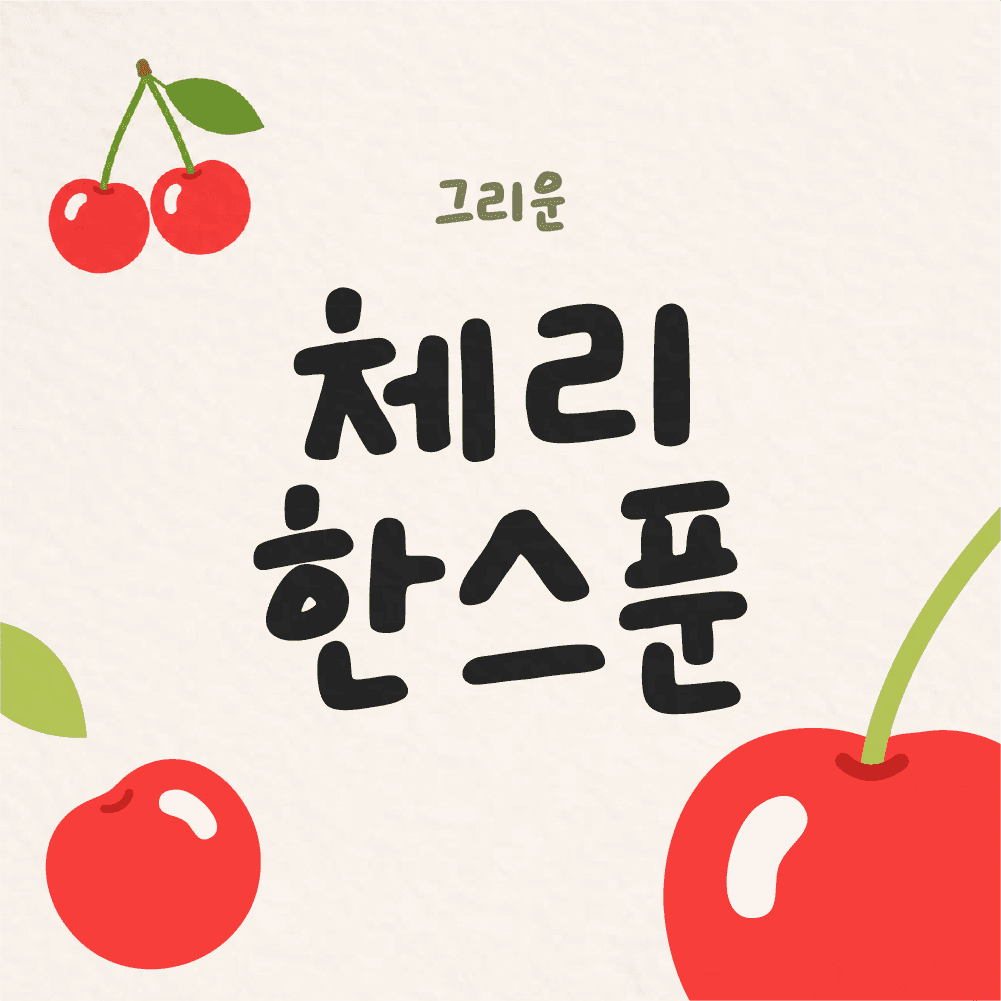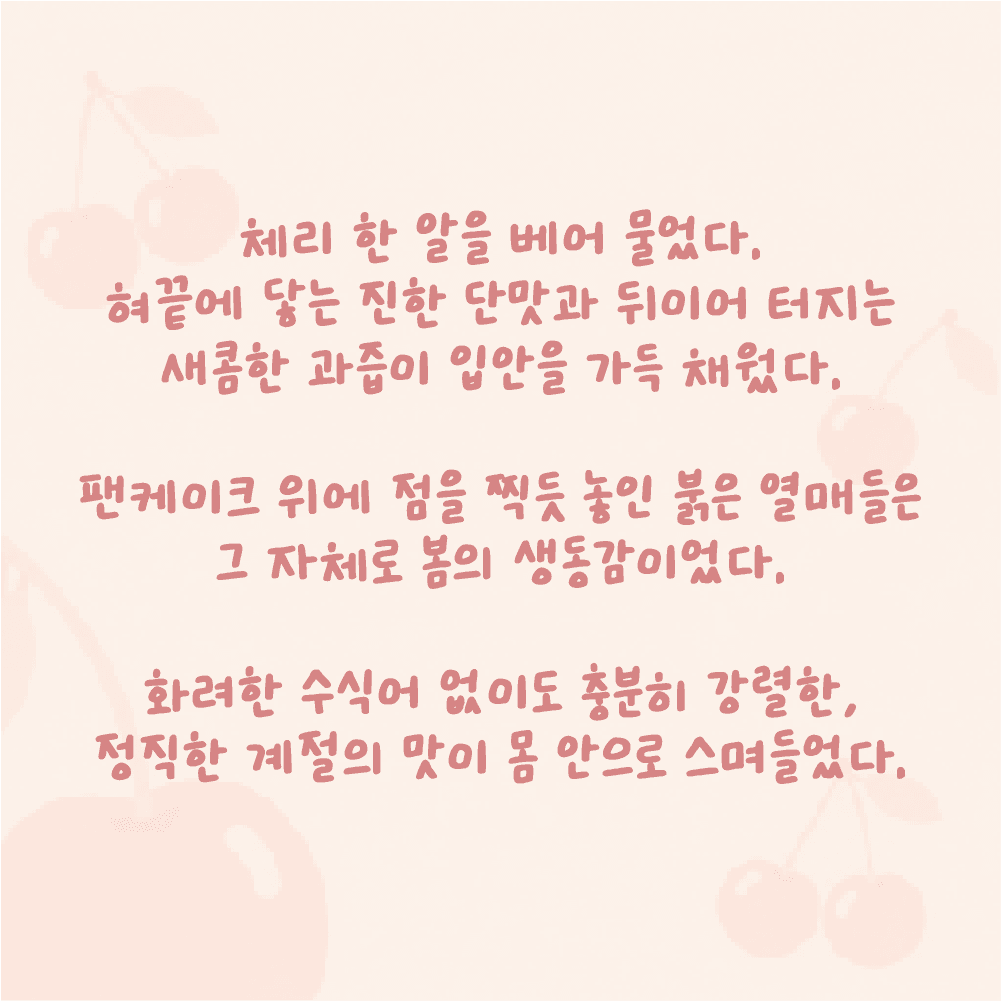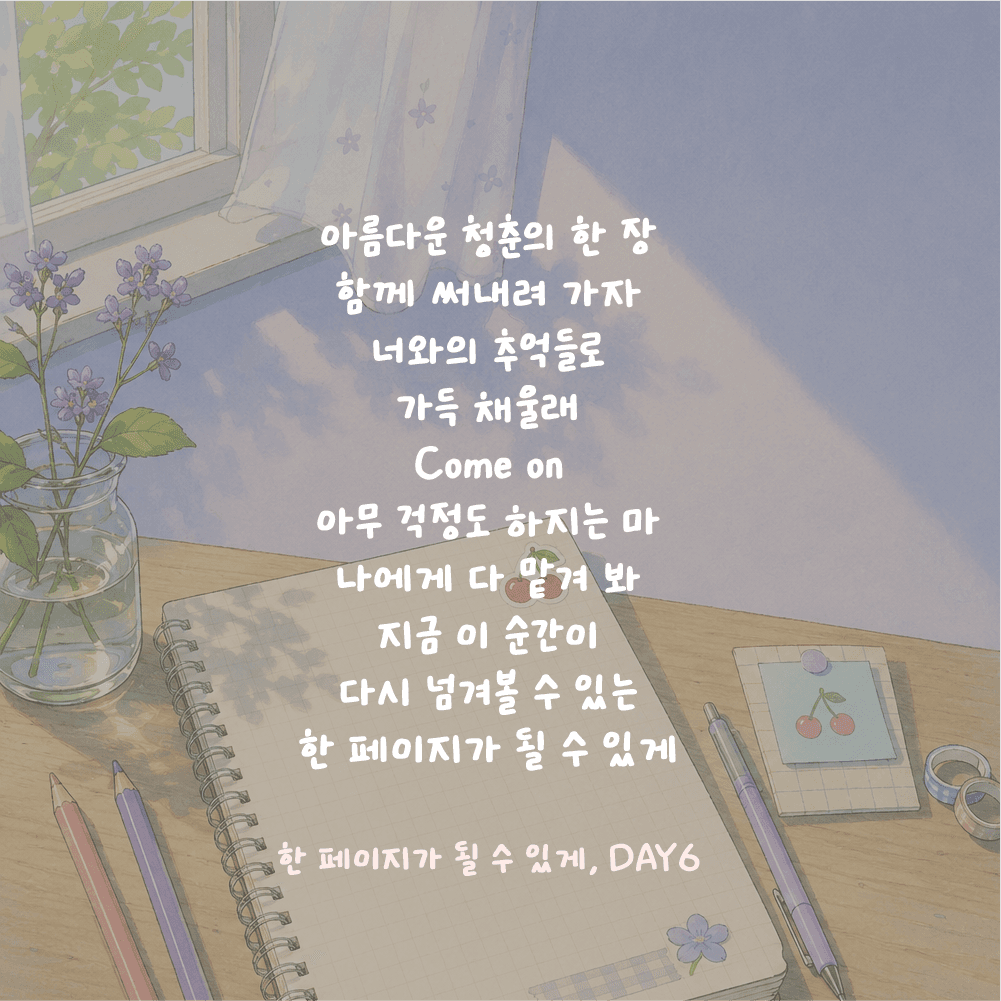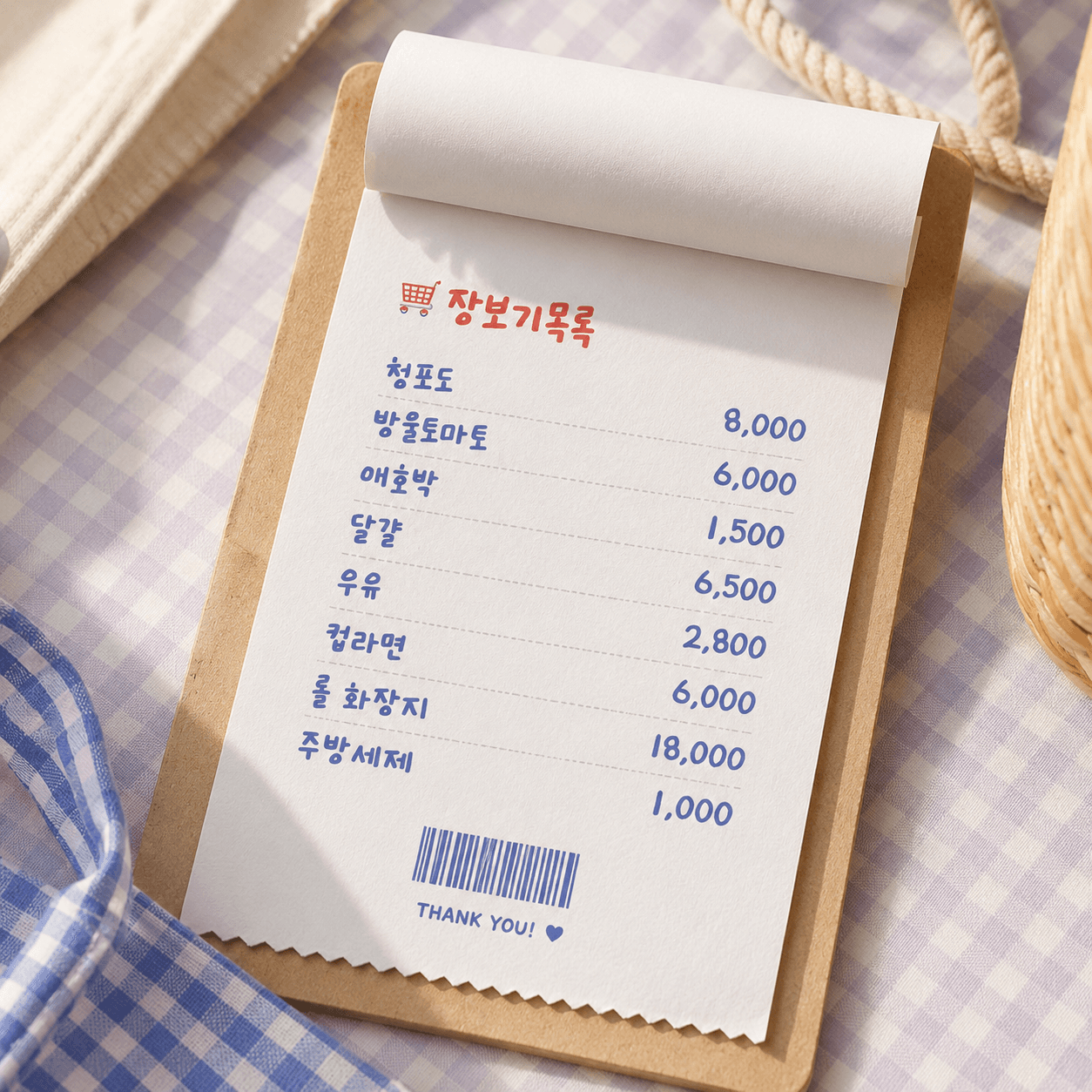
그리운 체리 한스푼
Griun Cherry 1 Spoon
그리운 체리 한스푼 소개
'그리운 체리 한스푼'은 이름처럼 달콤하고 따뜻한 감성이 묻어나는 서체입니다. 도톰하고 일정한 굵기로 시인성이 뛰어나며, 둥글둥글한 곡선미는 친근한 인상을 줍니다. 통통 튀는 발랄함, 체리 한 스푼을 더해 일상을 달콤하게 채워보세요.